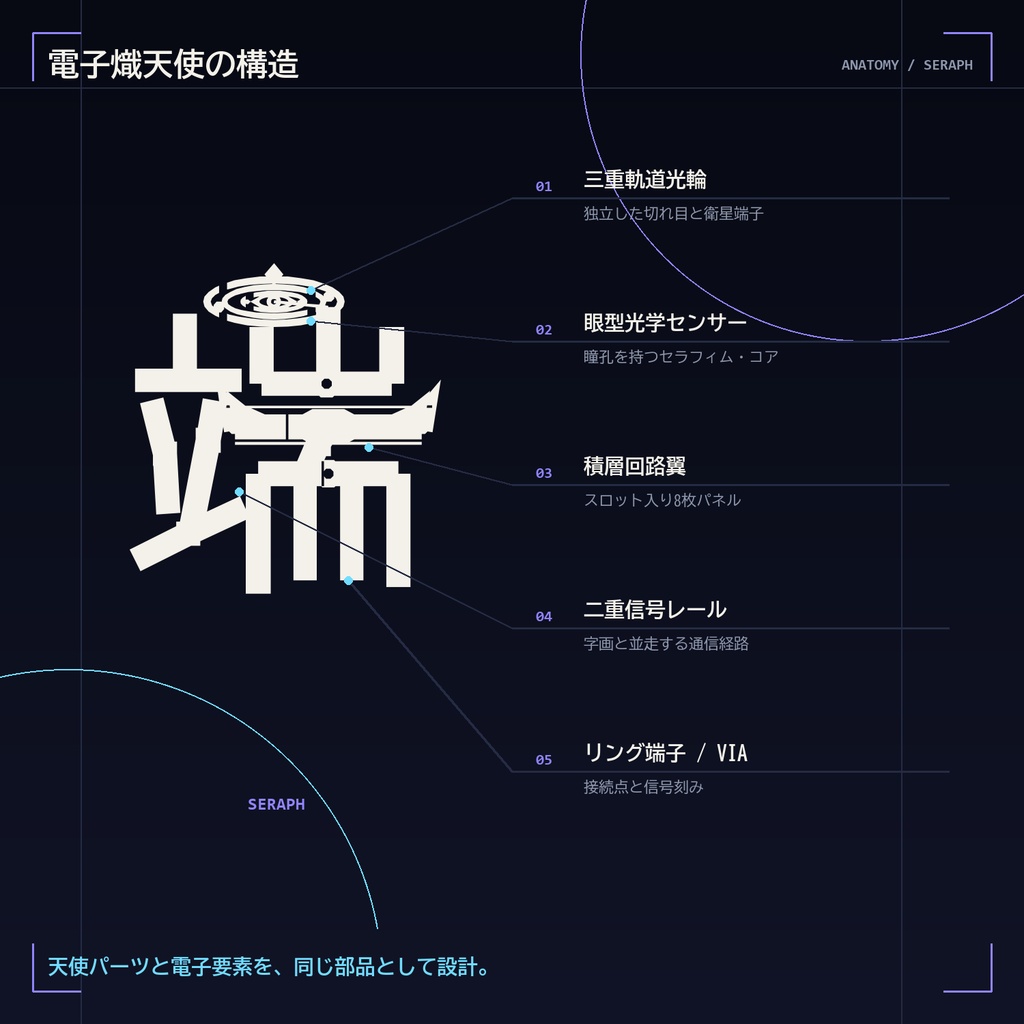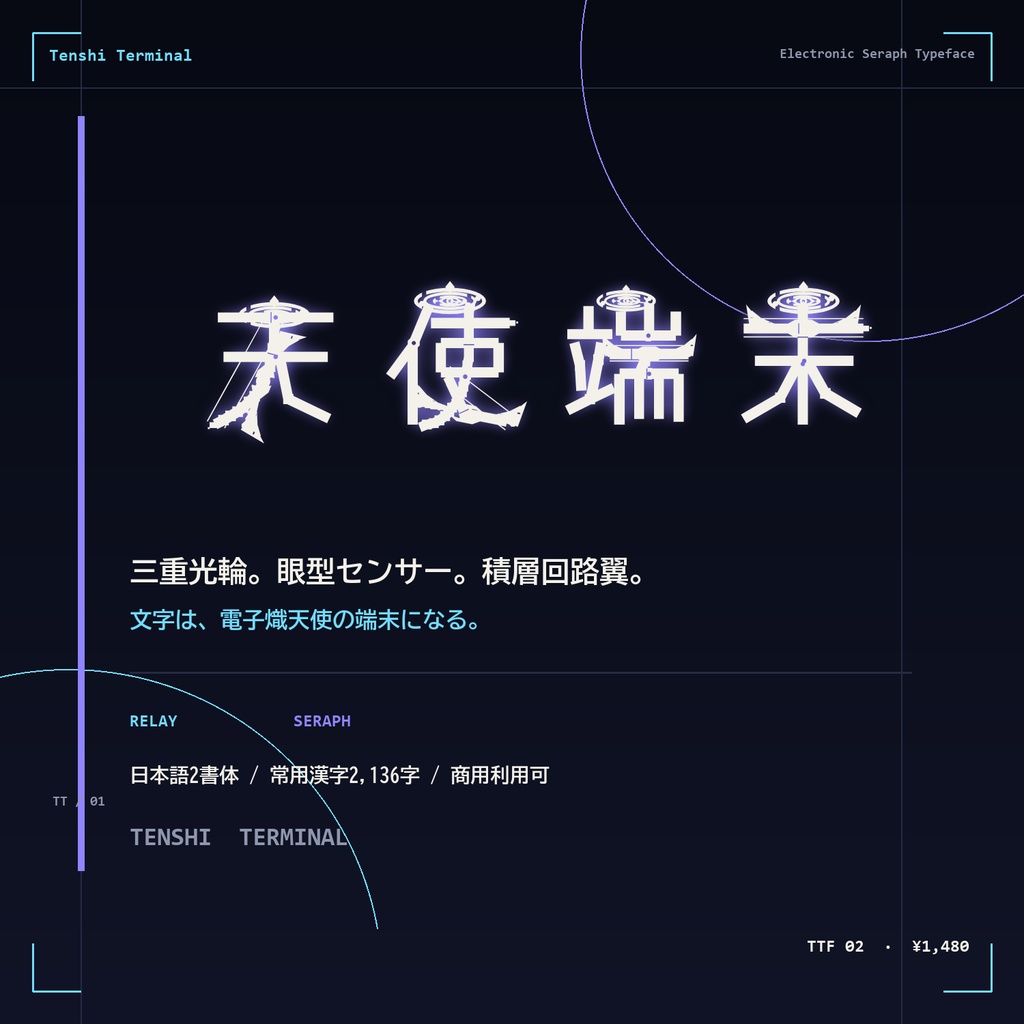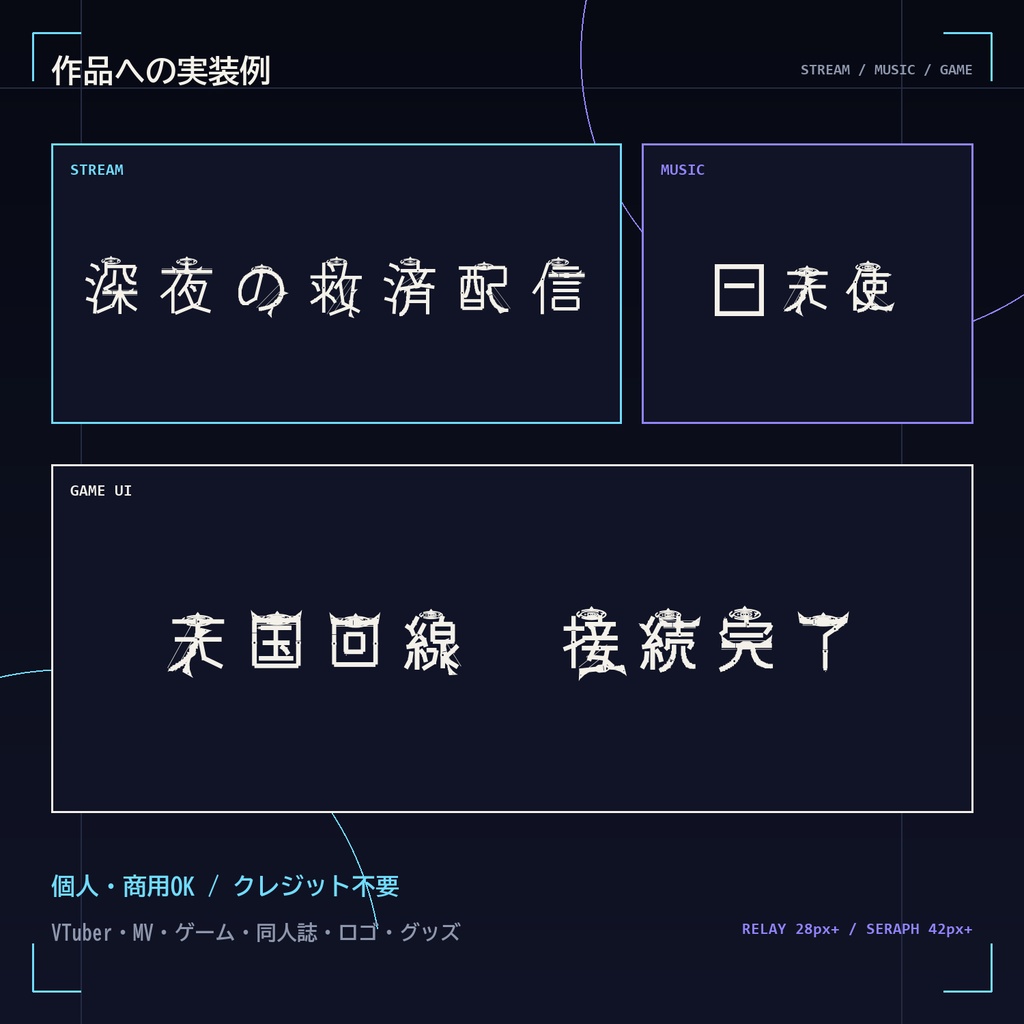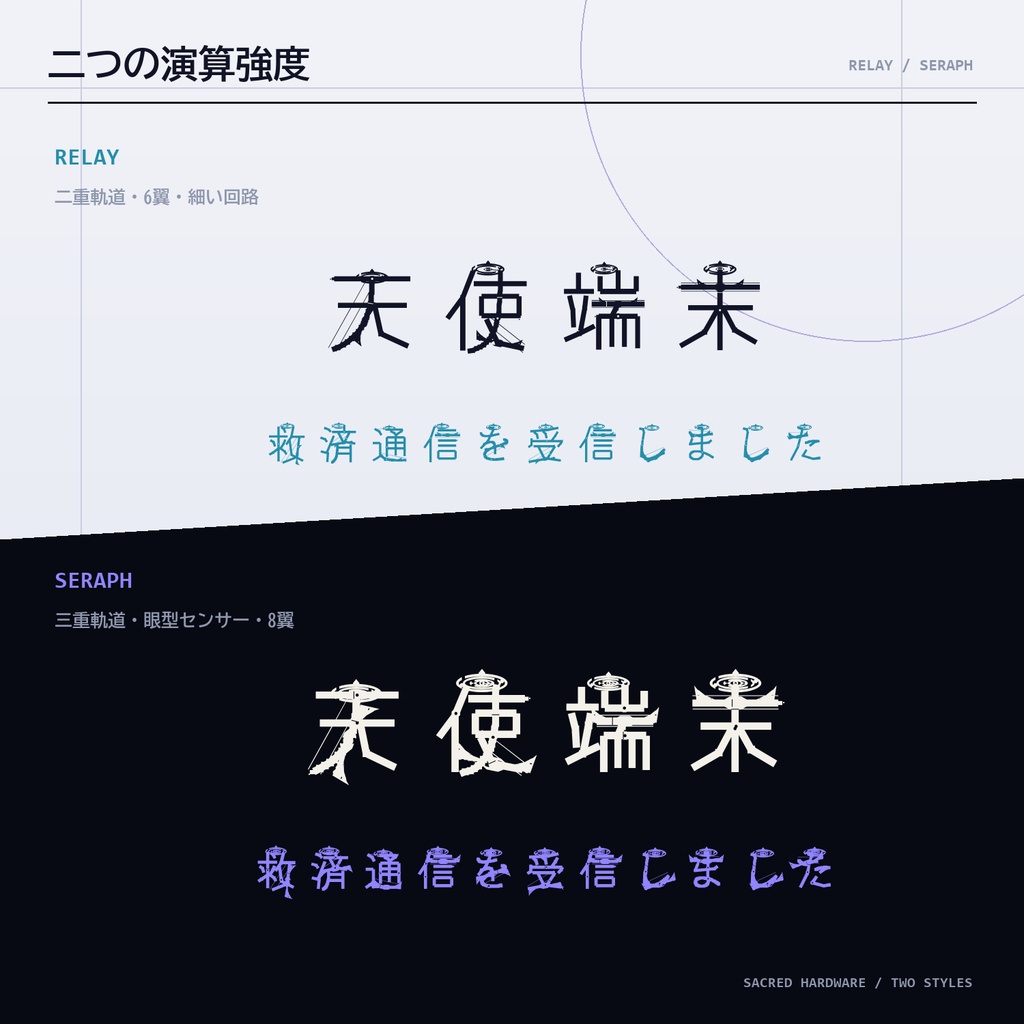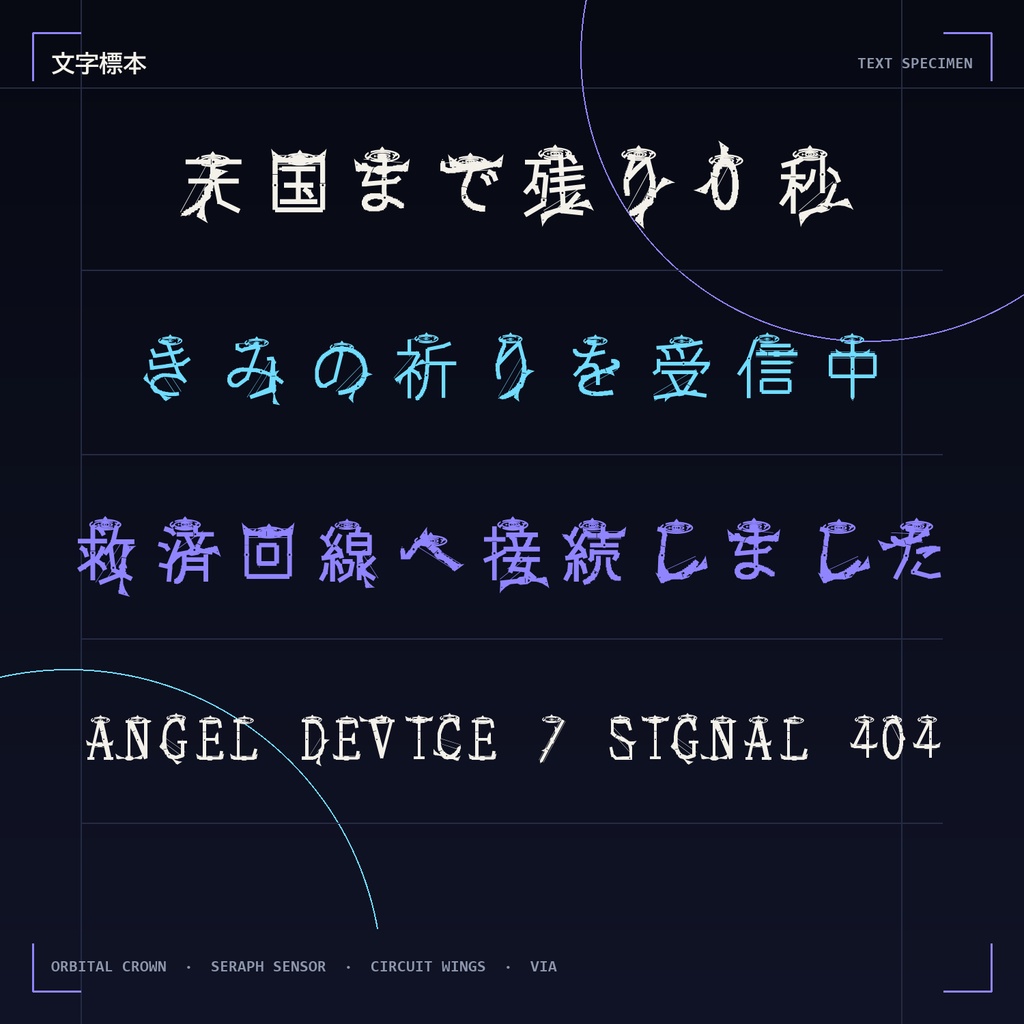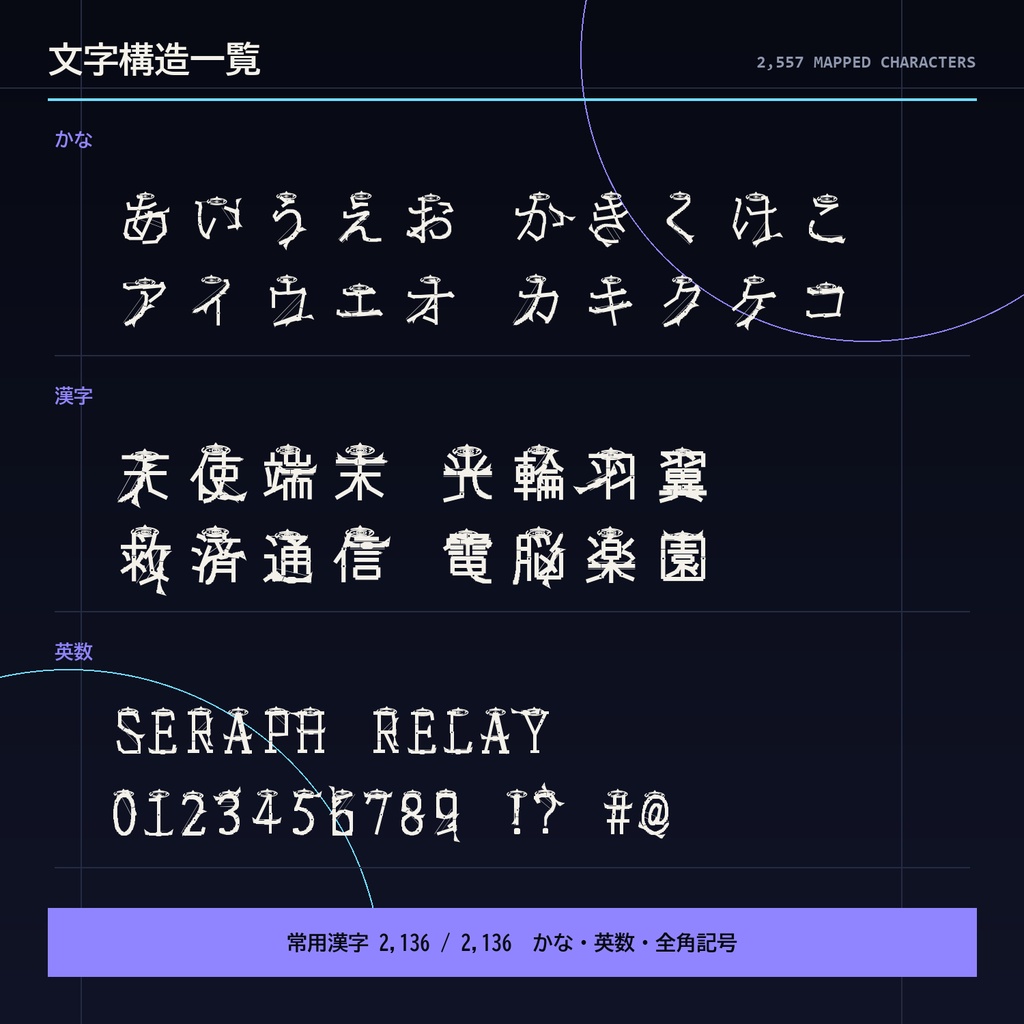
【電子熾天使フォント】天使端末|三重光輪・眼型センサー・回路翼の日本語2書体
これは、羽根を貼った文字ではない。 文字そのものが、電子熾天使の端末になる。 「天使端末 / Tenshi Terminal」は、天使の聖具と電子回路を一体の構造へ設計した日本語ディスプレイフォントです。 独立して回転する二重・三重軌道の光輪、瞳孔を持つセラフィム眼型センサー、基板のように積層した翼パネル、二重回路、端子パッド、信号刻みを全字へ統合。天使パーツと電子要素が別々の飾りではなく、一つの機械聖具として動作します。 ■ 2つの書体 ・RELAY / リレイ 細い二重回路、二重軌道光輪、6枚の翼パネル。告知、配信画面、動画テロップ向け。 ・SERAPH / セラフ 太い二重回路、三重軌道光輪、眼型センサー、8枚の翼パネル。ロゴ、ジャケット、ゲームタイトル向け。 ■ 収録 ・常用漢字2,136字 ・ひらがな / カタカナ ・半角・全角英数字 ・句読点、括弧、主要記号 ・TrueType(TTF)2書体 ■ 想定用途 VTuber・配信サムネ / 歌ってみた / MV / ゲームUI / TRPG 同人誌 / ジャケット / SNS告知 / ロゴ / ステッカー / アパレル ■ 利用条件 個人・商用OK。クレジット不要。 ロゴ、動画、ゲーム、印刷、配信、同人・商業作品に使用できます。 フォントファイルそのものの再配布・共有・転売は禁止です。 詳細はZIP内「ご利用規約.txt」をご確認ください。 ■ 推奨サイズ RELAY 28px〜 / SERAPH 42px〜 光輪と羽根を含む装飾書体のため、長文本文よりタイトル・見出し・短いコピーに適しています。 ※GlyphWiki由来のKAGE骨格データを用い、独自の電子熾天使字形へ再構成しています。GlyphWikiライセンス原文を同梱しています。